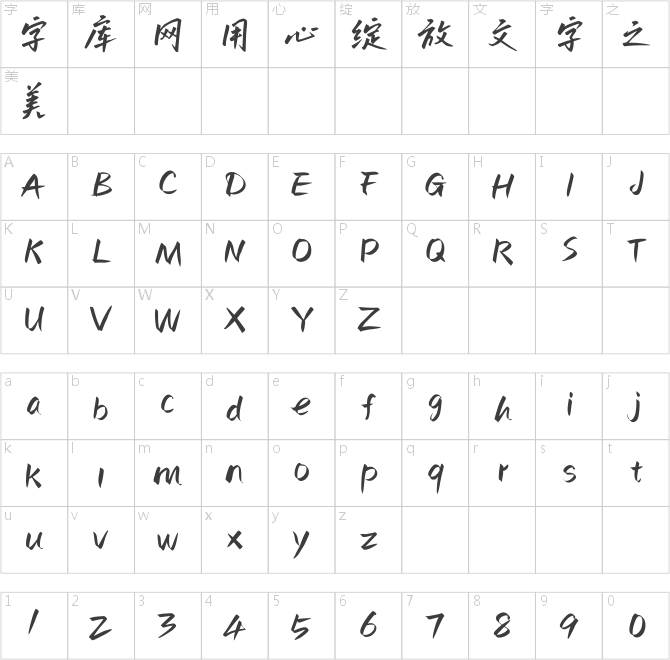
點(diǎn)字熱烈體 詳情頁
字體名稱: 點(diǎn)字熱烈體
點(diǎn)字熱烈體字體字庫是一款讓人賞心悅目、百看不厭的中文字體,適合各類廣告和產(chǎn)品包裝設(shè)計(jì)應(yīng)用,字體大小7.92MB,格式為ttf字體,上傳用戶是一直在守護(hù),作者/版權(quán)方為點(diǎn)字